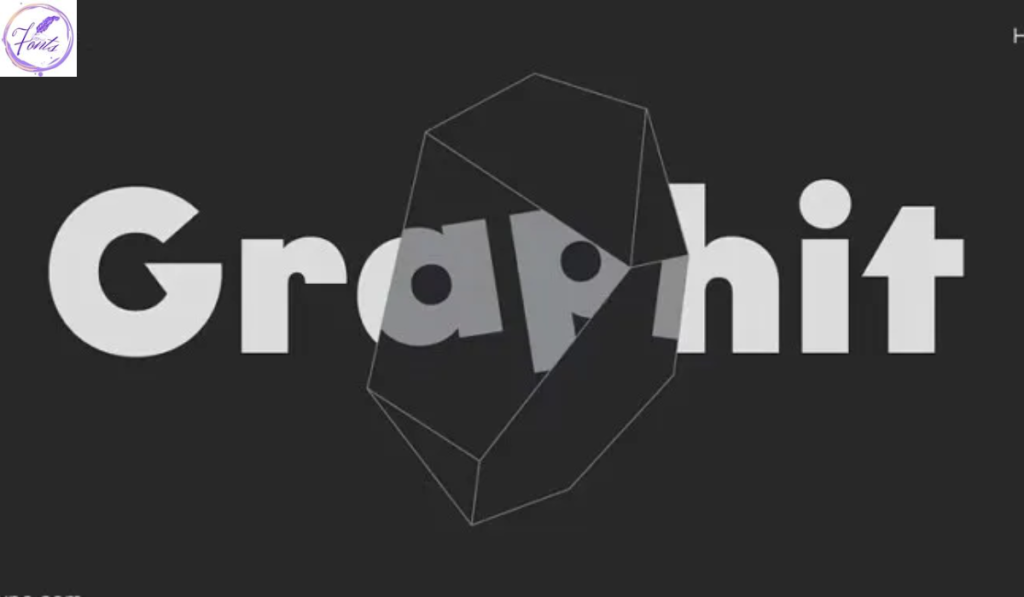
Graphit Black Font Family việt hóa
Tác giả: Livius Dietzel, Tom Hossfeld
Ngày phát hành: 2014
Ngôn ngữ: Tiếng Việt, nhiều ngôn ngữ khác
Bộ Font: Graphit
Phân loại: Cá tính, độc đáo
Kiểu chữ: Sans-serif (không chân)
Độ dày: Black
Graphit black font là một font chữ mạnh mẽ và đầy ấn tượng, được thiết kế để làm nổi bật các tiêu đề và nội dung quan trọng. Được tạo ra bởi một nhóm các nhà thiết kế tài năng, font này mang lại sự kết hợp hoàn hảo giữa tính thẩm mỹ và tính ứng dụng cao. Với các đường nét dày dặn và rõ ràng, graphit black font dễ dàng thu hút sự chú ý và tạo điểm nhấn cho bất kỳ dự án thiết kế nào. Phiên bản Việt hóa của font này đảm bảo hiển thị đầy đủ các ký tự tiếng Việt, giúp người dùng Việt Nam dễ dàng sử dụng và tạo ra những sản phẩm đẹp mắt.
Graphit black font nhận được nhiều lời khen ngợi từ cộng đồng thiết kế nhờ vào tính năng đa dụng và vẻ đẹp mạnh mẽ của nó. Các nhà thiết kế đánh giá cao sự rõ ràng và dễ đọc của font này, ngay cả khi sử dụng ở kích thước nhỏ. Điều này làm cho graphit black font trở thành lựa chọn lý tưởng cho các tiêu đề, bảng hiệu và các dự án cần sự nổi bật. Phiên bản Việt hóa của font cũng được đánh giá cao vì giữ nguyên được đặc trưng của bản gốc, đồng thời bổ sung đầy đủ các ký tự cần thiết cho tiếng Việt.